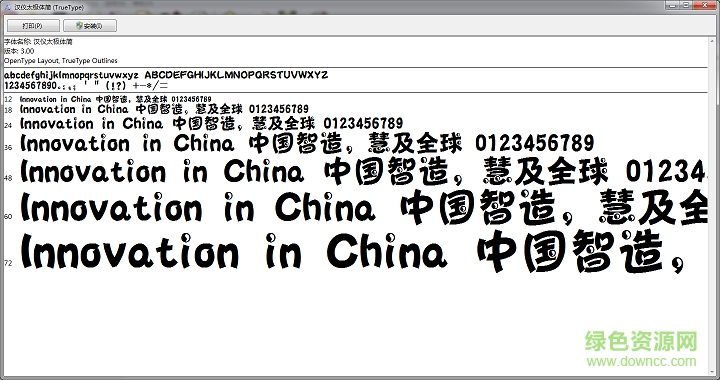
hy03gj
hy03gj字體又稱漢儀太極體簡(jiǎn),是提款非常有特色的電腦中文字體,字形圓潤(rùn)可愛(ài),適合用來(lái)進(jìn)行各種藝術(shù)創(chuàng)作,有需要的朋友歡迎來(lái)綠色資源網(wǎng)下載使用!
hy03gj字體簡(jiǎn)介
hy03gj字體是一款比較有特色的字體,字體的點(diǎn)是一個(gè)太極符號(hào),字體總體看起來(lái)是一款偏向于可愛(ài)類(lèi)型的字體,應(yīng)該比較適合女孩子使用的。